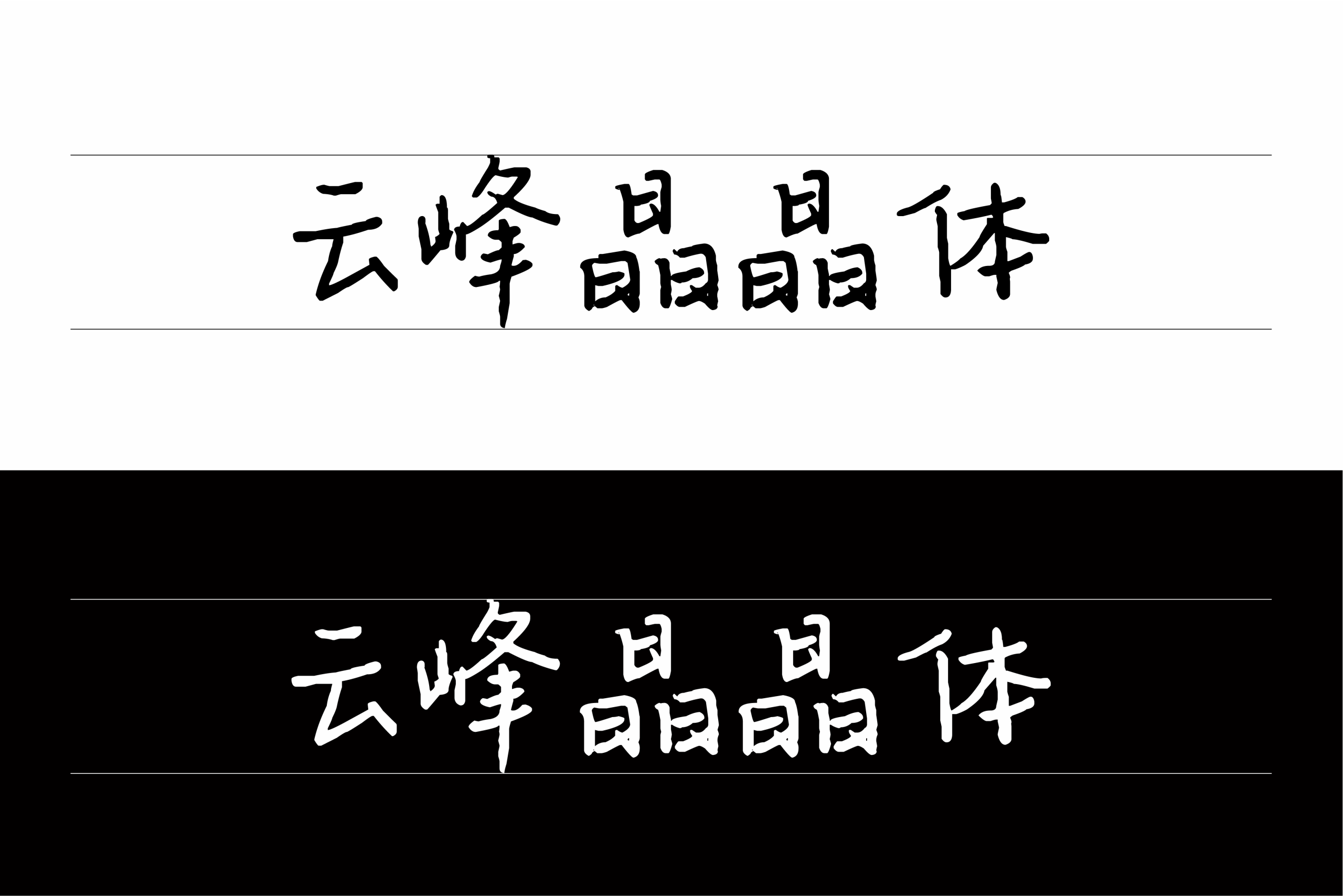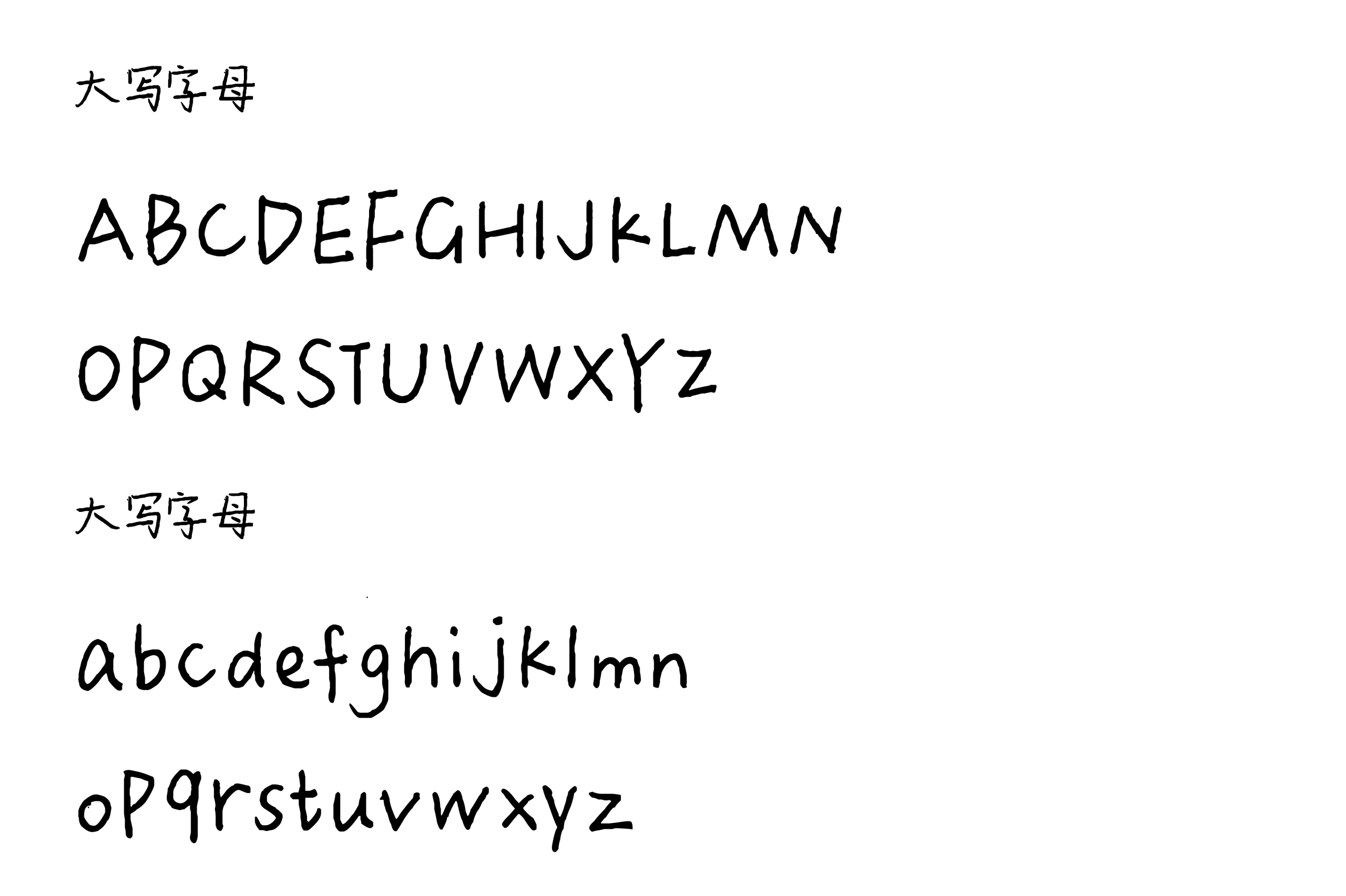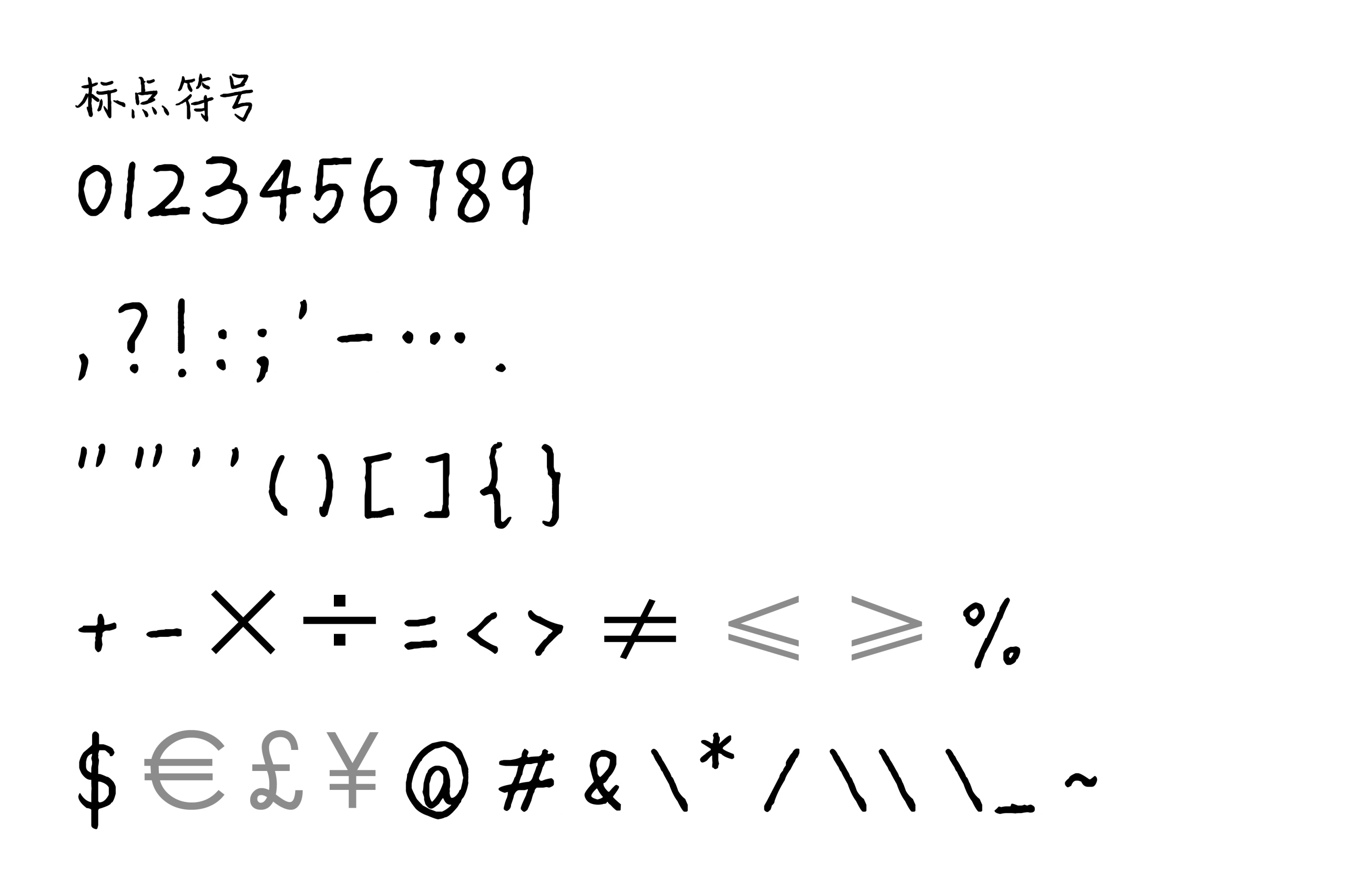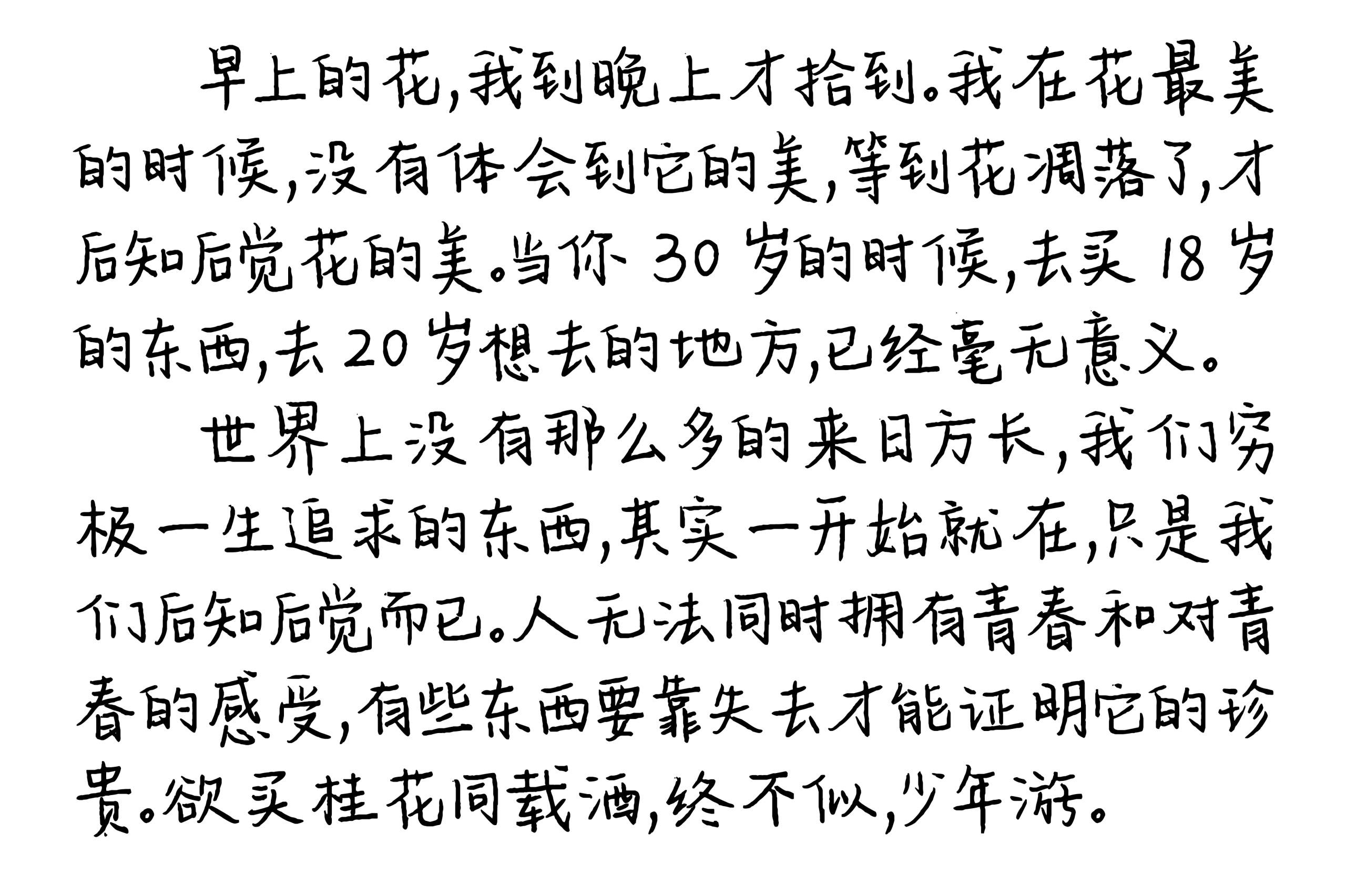
云峰晶晶体
云峰晶晶体是一款由云峰字库推出的手写风格字体。不同于规整、标准化的印刷字体,这款字体保留了较为明显的手写痕迹,字形结构自然舒展,笔画粗细与连接方式带有一定的随意性,整体呈现出轻松、质朴而富有亲和力的视觉气质。
从字体展示来看,云峰晶晶体具有较强的个人书写特征。中文字符的笔画并不刻意追求绝对工整,部分转折、收笔和结构处理保留了手写状态下的自然变化,使文字呈现出类似学生时代课堂笔记、随手记录时的书写感觉。这种并不刻意追求规整的字形,反而让字体拥有更加鲜明的情绪表达,也让普通文字具备了一定的生活感和温度。
在字形设计上,云峰晶晶体整体以较为简洁的线条构成,笔画轮廓清晰,同时通过不同程度的弯曲、倾斜和不规则变化削弱了机械感。与传统黑体、宋体等标准化字体相比,它的视觉重心更加轻松,适合用于需要营造自然、随性和年轻化氛围的设计作品。
除了中文字符之外,云峰晶晶体还提供英文字母字符,并包含大写与小写字母。英文字形同样延续了中文部分的手写特征,字母之间具有较明显的书写感,在中英文混合排版中能够保持相对统一的视觉风格。因此,在标题、短句、装饰性文字以及中英文组合设计中,都能够形成较为完整的手写字体效果。
从应用场景来看,云峰晶晶体比较适合用于具有生活气息和轻松氛围的视觉设计。例如手账、文具、校园主题设计、社交媒体配图、活动海报、包装视觉、短视频封面以及个人作品集等,都可以利用其自然的手写质感增强画面的亲和力。如果设计主题强调“记录”“青春”“日常”“随手写下的一句话”等情绪,这款字体也能够较好地契合整体视觉方向。
需要注意的是,手写字体虽然具有较强的个性,但并不适合所有文字排版场景。对于正文、长篇文章以及需要高度规范化阅读体验的内容,建议优先选择阅读性更强的常规字体;而在标题、短文案、重点信息和装饰性文字中使用云峰晶晶体,则更容易发挥其视觉特点。
总体而言,云峰晶晶体并不是一款强调标准化与严谨排版的字体,而是通过保留手写过程中的自然变化,营造一种轻松、朴素且带有学生时代记忆感的视觉效果。如果正在寻找一款具有真实手写气息、能够弱化数字字体机械感的中文字体,云峰晶晶体会是一个值得关注的选择。